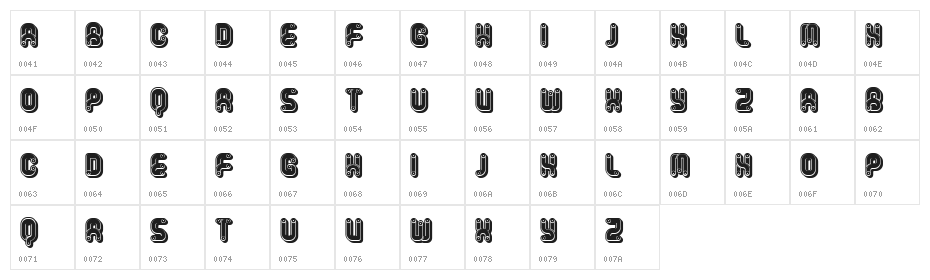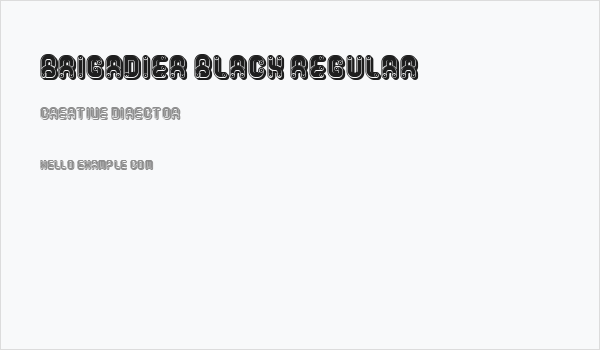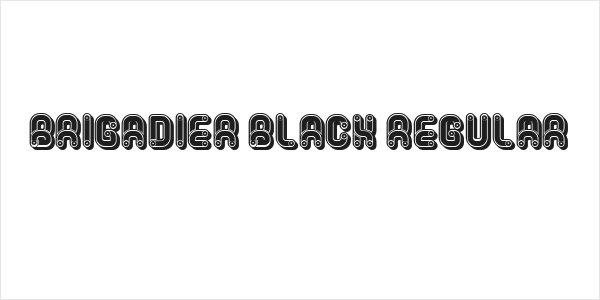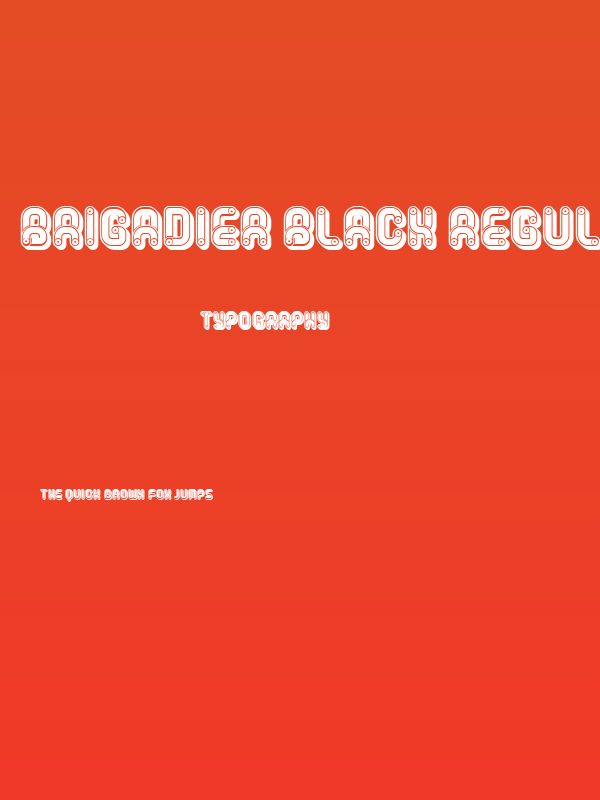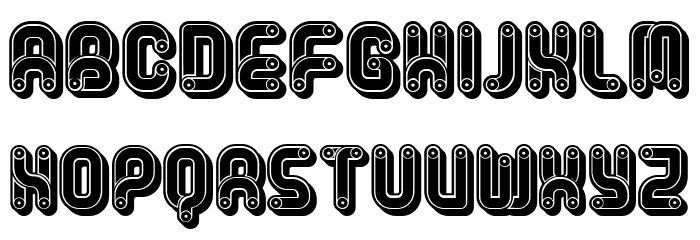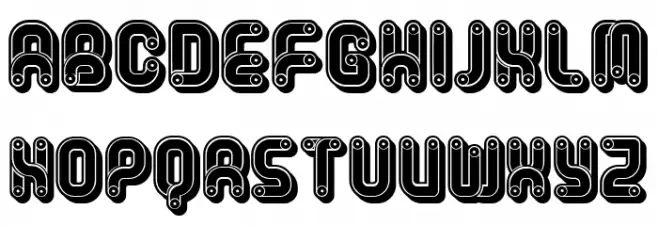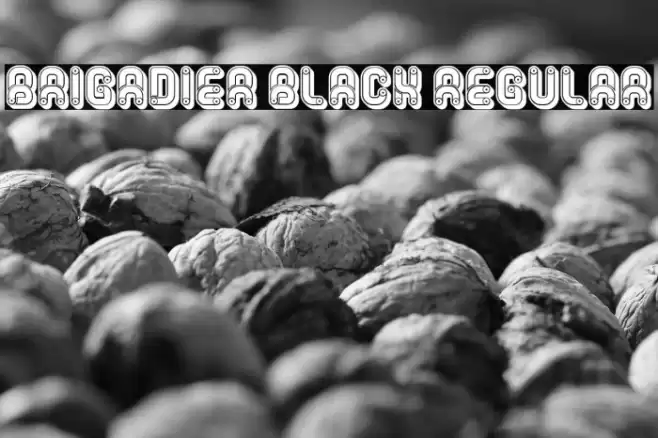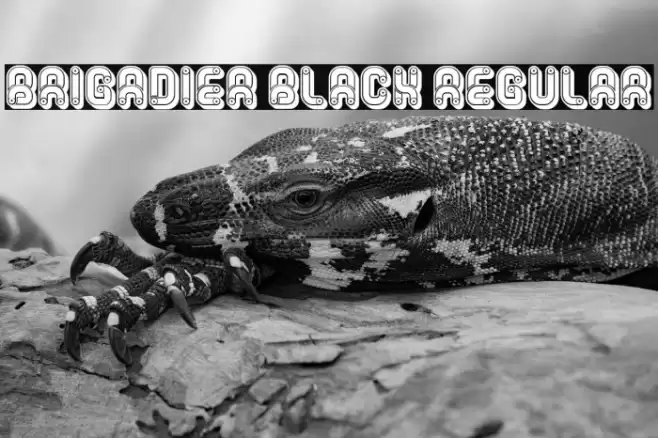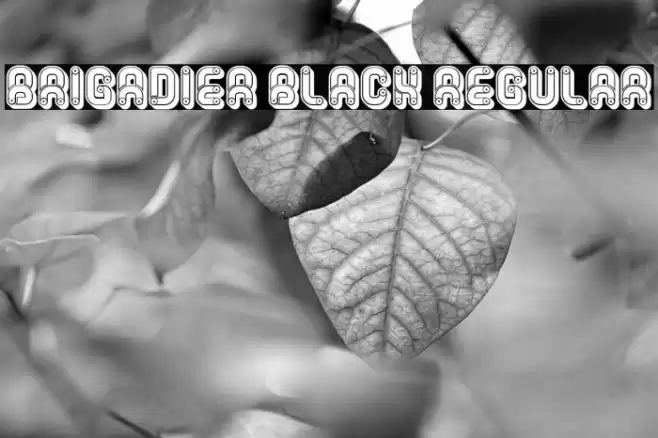
Brigadier Black Regular Font
| Stil general | Modern, Industrial |
| Caz de utilizare | Headlines, Logos, Branding |
| Proiecte propuse | Ideal for branding, posters, signage, and any project requiring a bold, industrial aesthetic. |